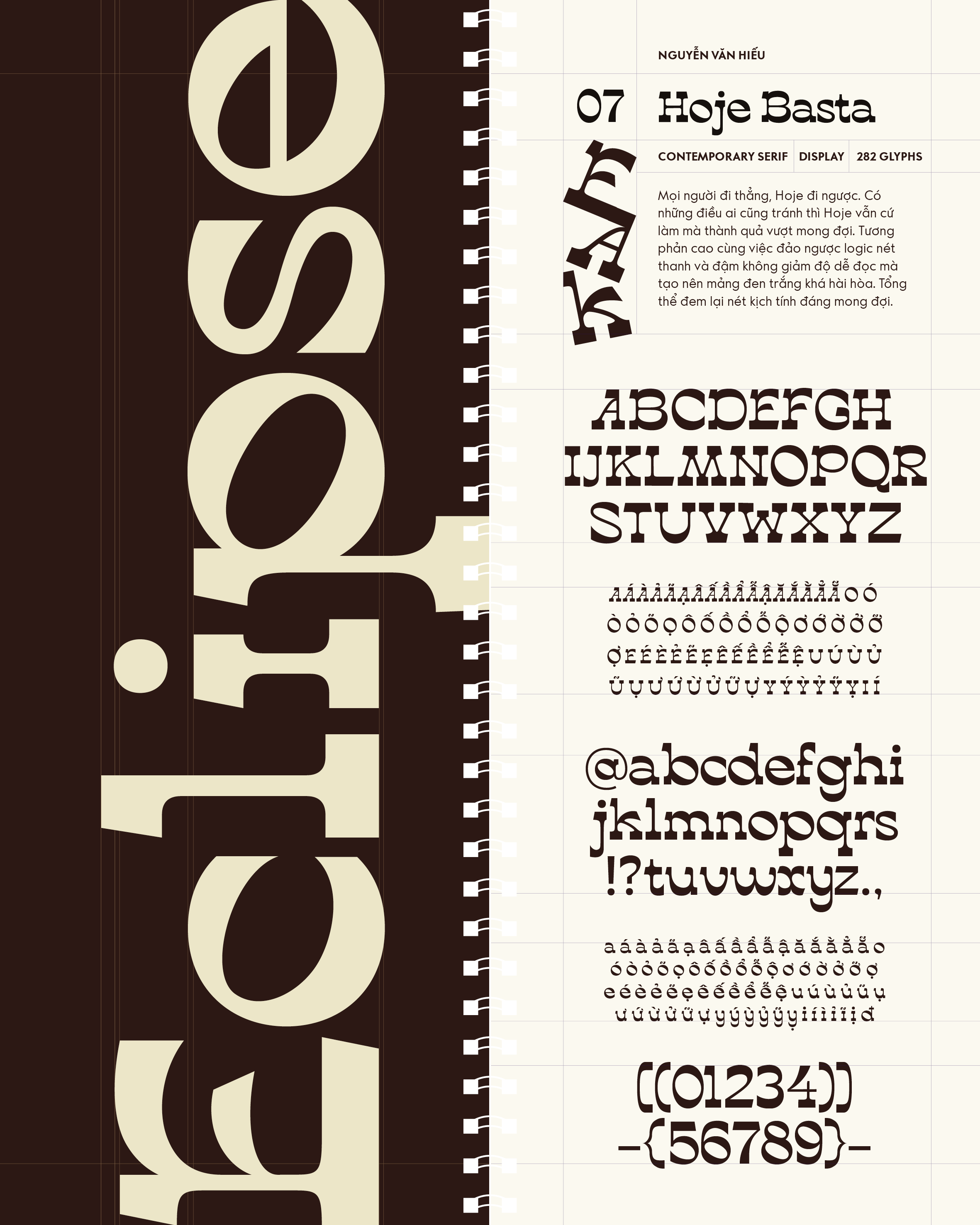
Hoje Basta
Về Hoje Basta: Mọi người đi thẳng, Hoje đi ngược. Có những điều ai cũng tránh thì Hoje vẫn cứ làm mà thành quả vượt mong đợi. Tương phản cao cùng việc đảo ngược logic nét thanh và đậm không giảm độ dễ đọc mà tạo nên mảng đen trắng khá hài hòa. Tổng thể đem lại nét kịch tính đáng mong đợi.
Contemporary Serif
Display
Nguyễn Văn Hiếu